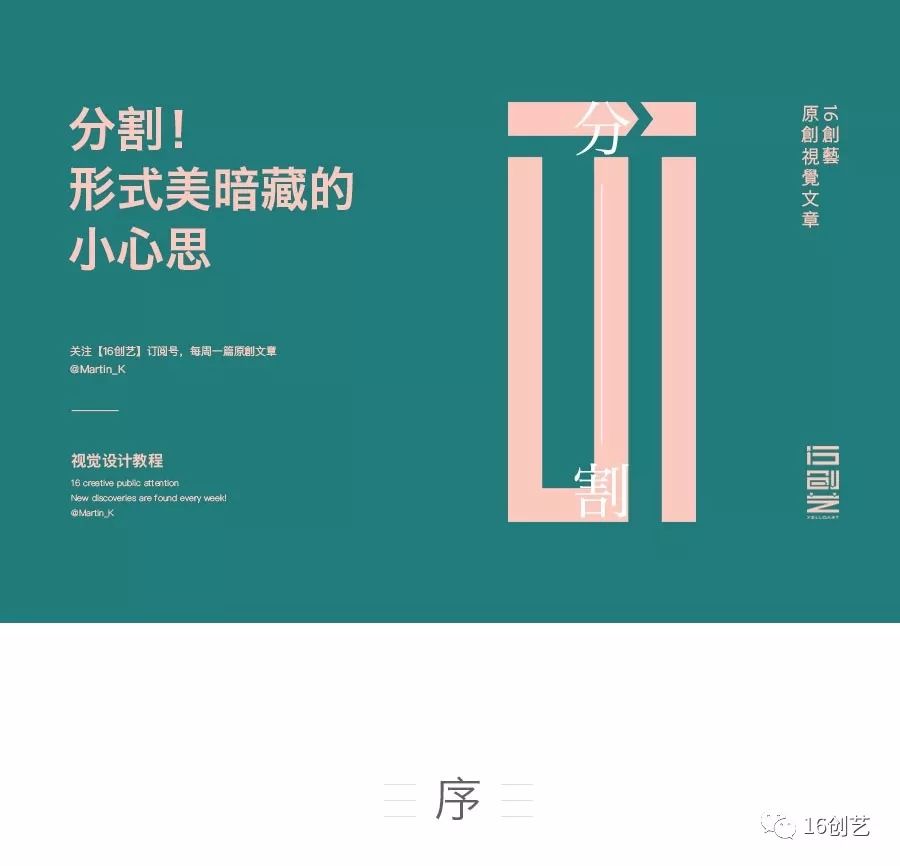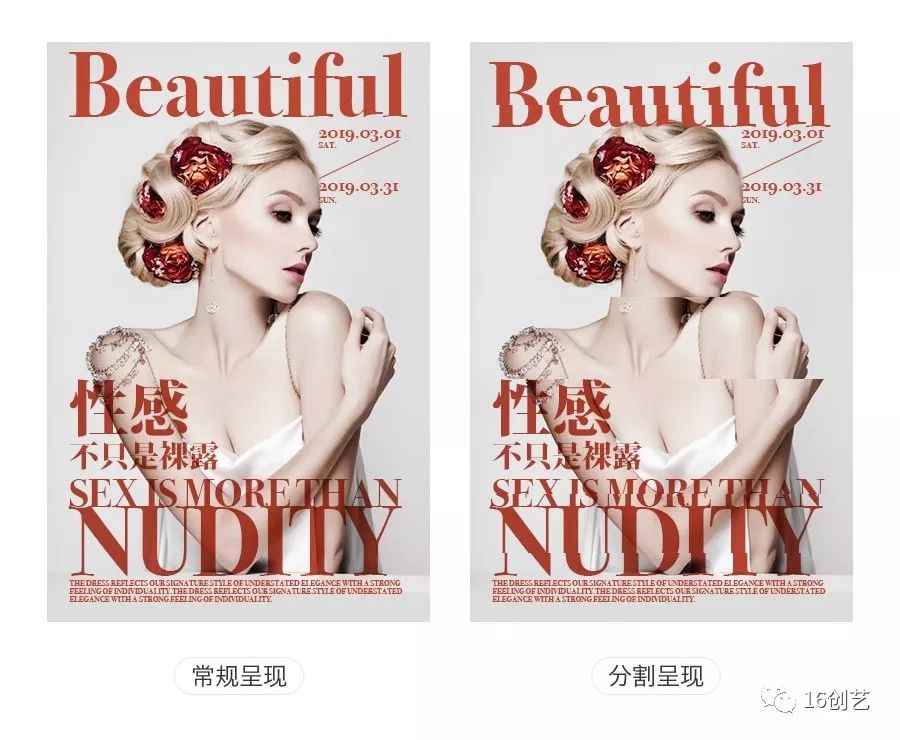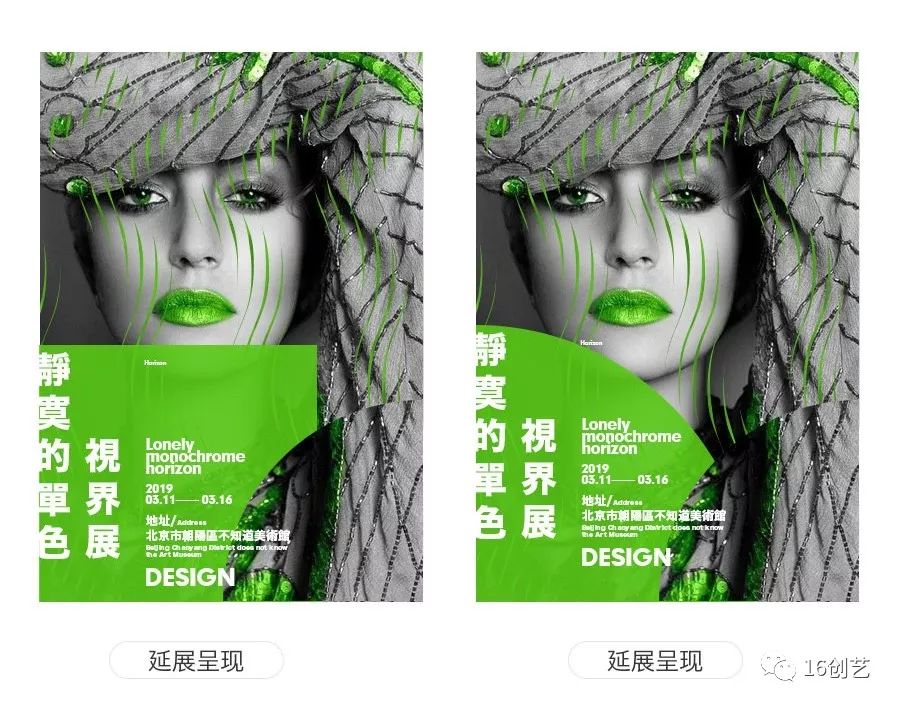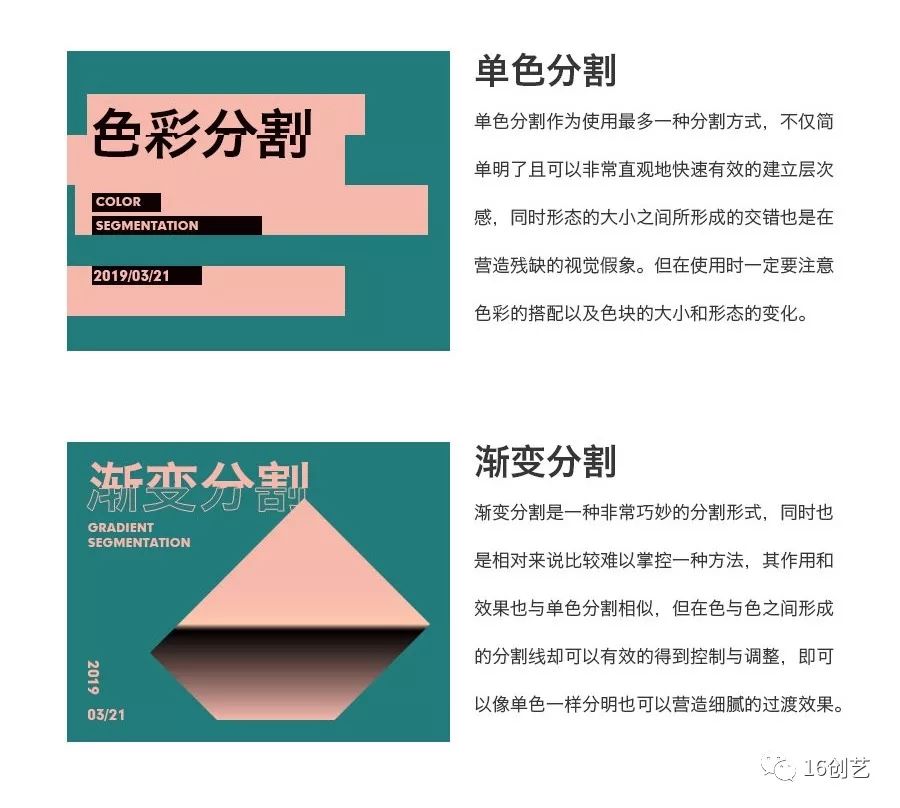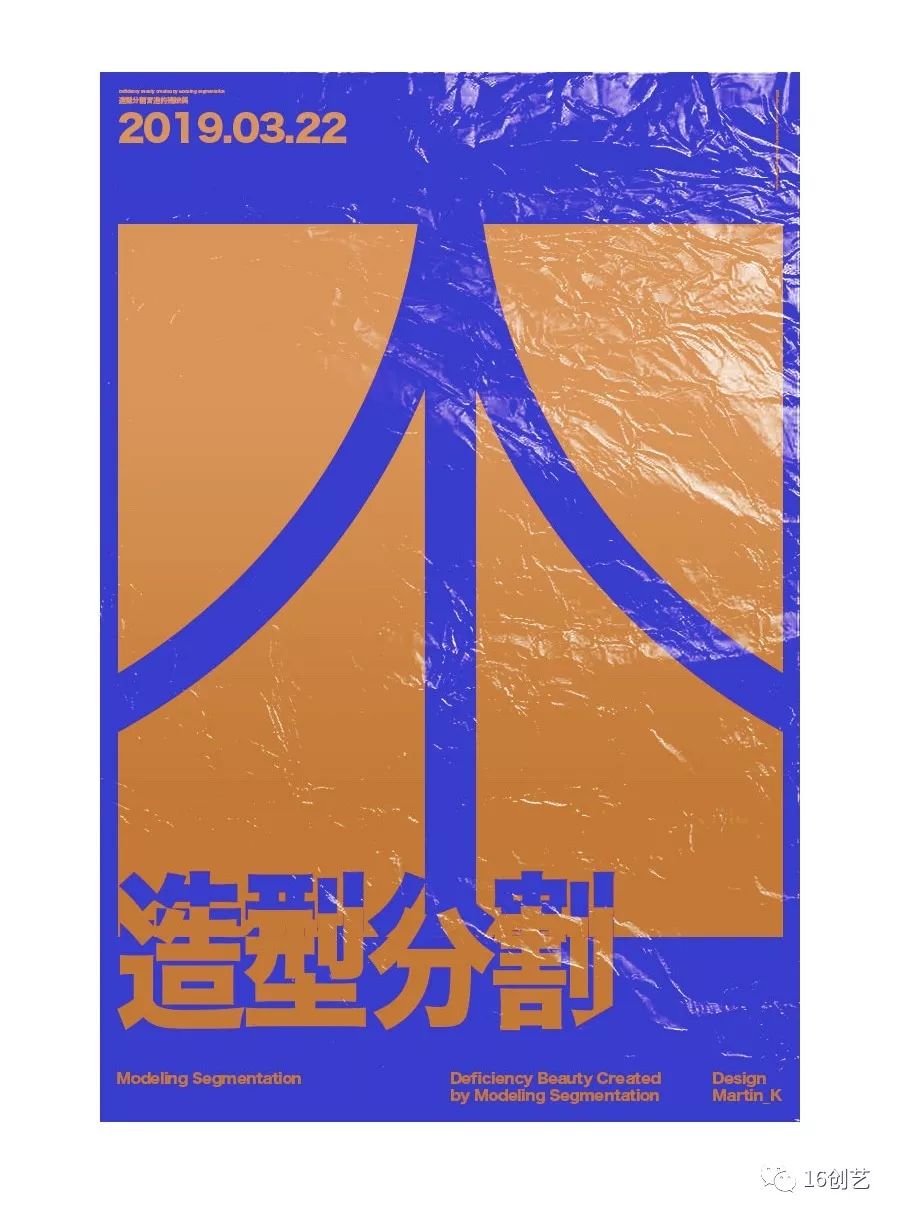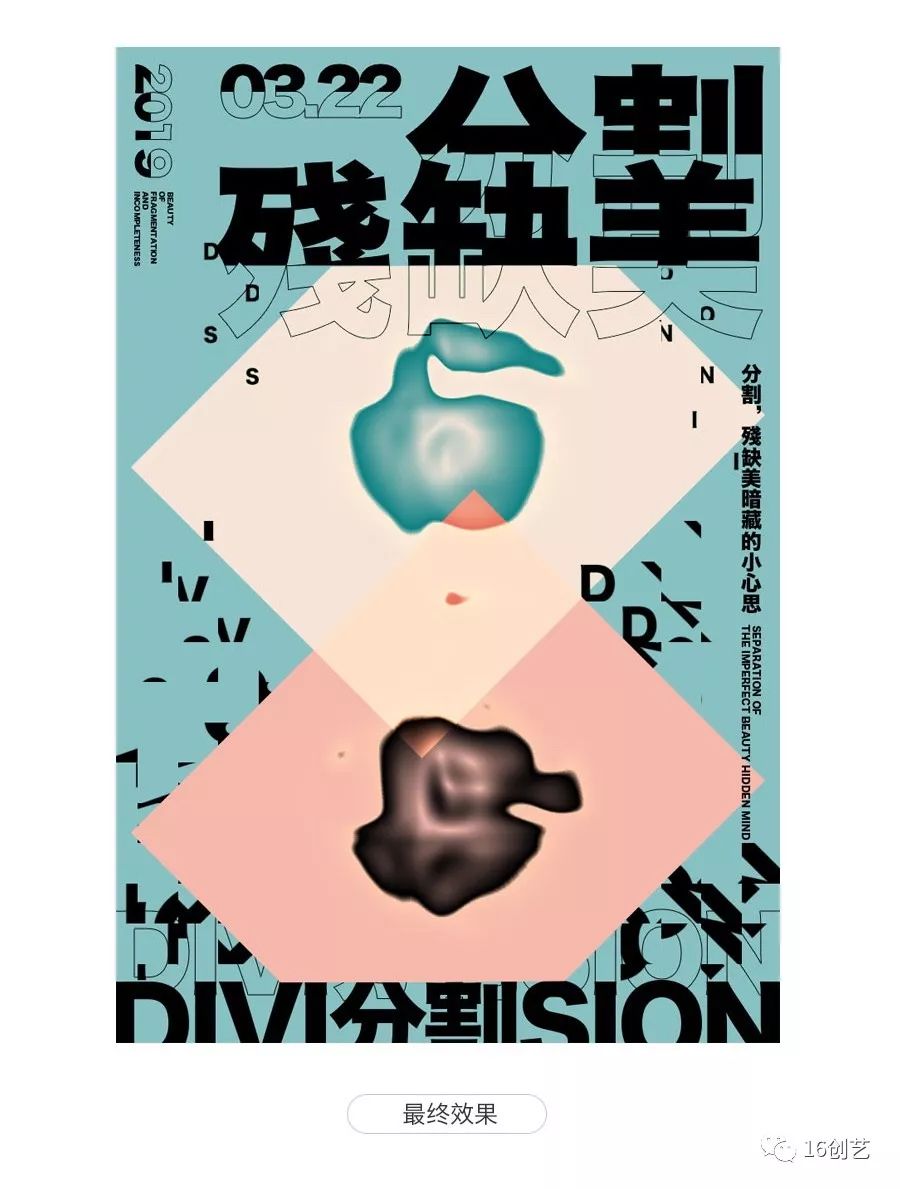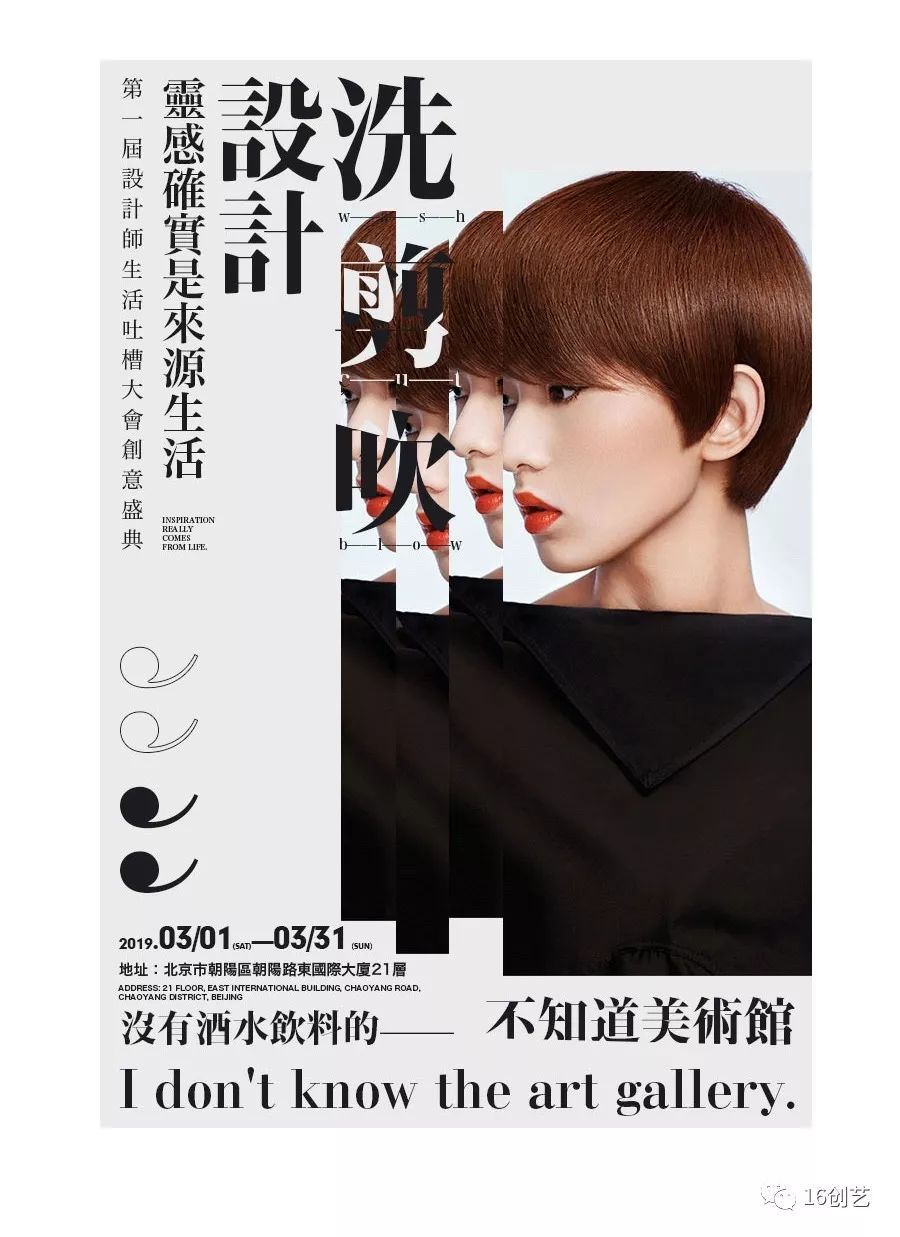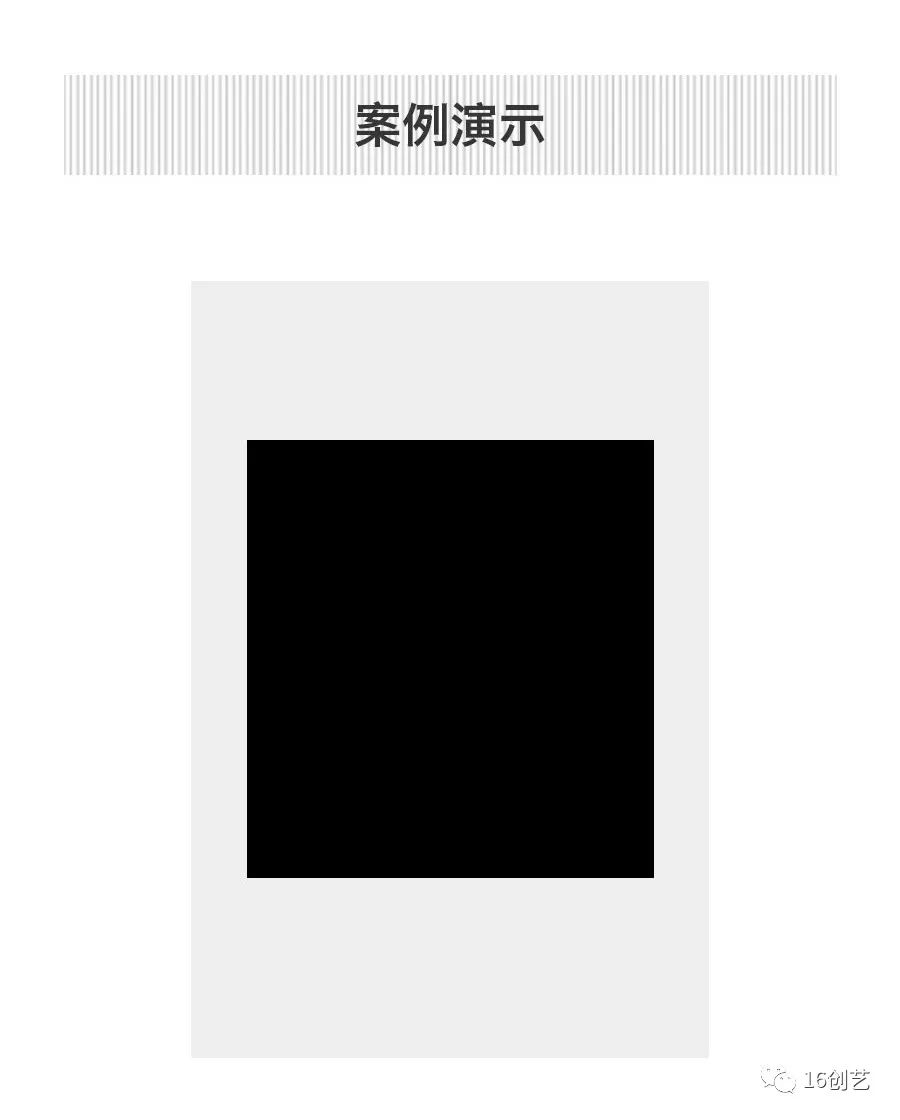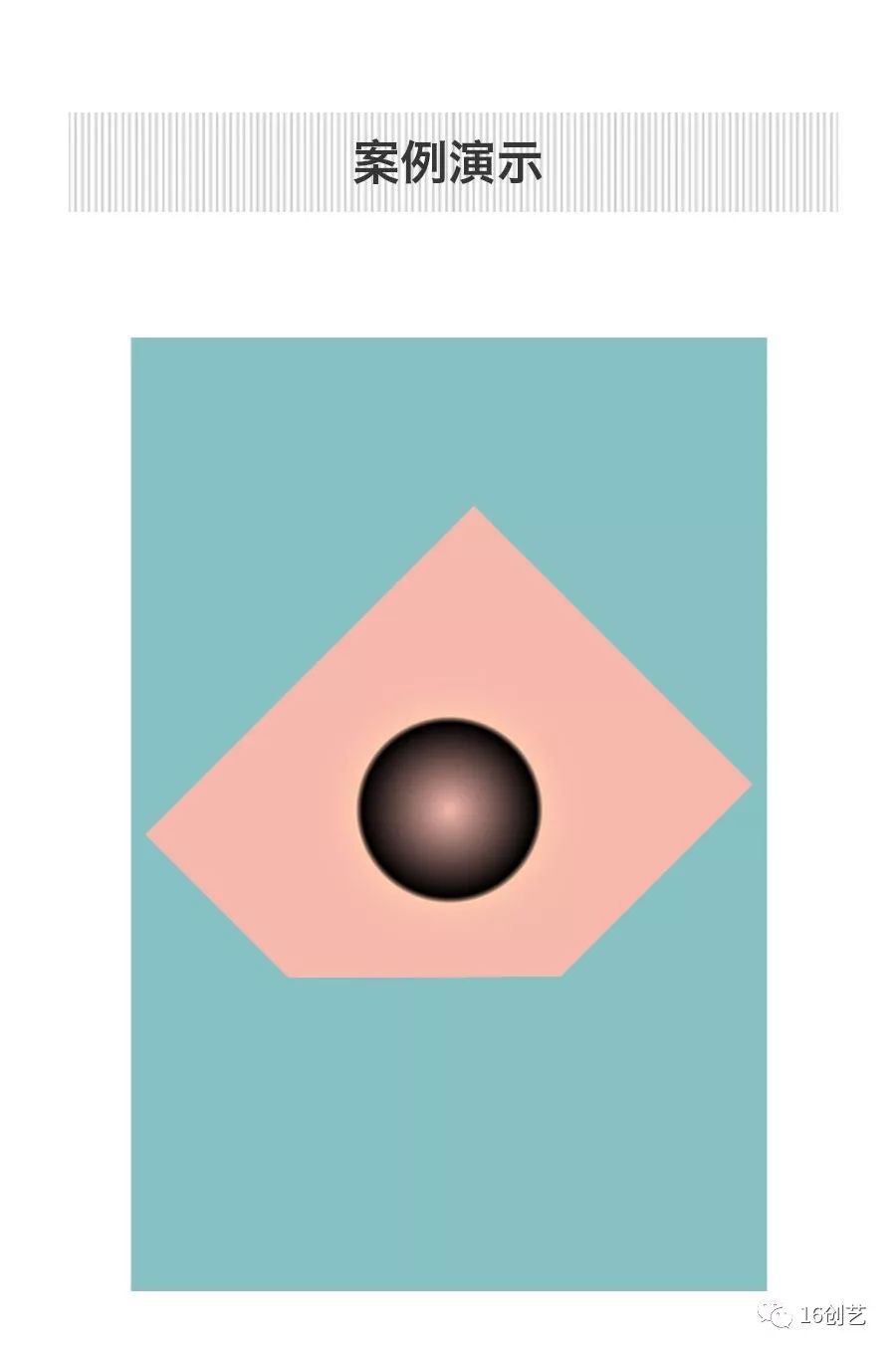
什么事分割?一篇文手把手教你所有的分割形式~
在日常生活中我们经常会看到破裂的事物,甚至在我们一不小心的时候就会把喜爱的杯子掉在地上摔碎了,或者在生气的时候把东西给撕烂,而这些看起不起眼的事情亦或者是人们在发泄情绪时的行为所产生的结果,在艺术领域却是有着不同的作用和价值,甚至是成为艺术创作者的神秘武器,而对于设计创作者来说则是把这种捕捉到的瞬间美以切割艺术表现的手法定格在创作的作品当中,用于表达和记录生活中因某些破坏行为而产生的残缺美,同时也是在遵循一定的设计准则、视觉感知的基础上对画面中出现的元素加以破坏,更好的演绎残缺美营造画面冲击力,也是基于小心思加法的基础上做减法。
分割即是在限定的空间内把完整的物体或者空间按照一定的方法加以破坏使其形成新的整体形态,并利用人眼自动补齐和联想的视觉规律,形成分而不离,割而不断的特点,营造一种残缺的、破坏的艺术美,同时也是提取生活中经常会出现的一种破坏后形成的自然现象作为常用的视觉表现手段应用在设计中,以更好的丰富艺术作品的创作,不仅可以营造残缺美还可以更好的赋予作品想象的空间,同时也是设计中极具细腻小心思的体现。
空间分割就是我们经常会提到的版式编排设计,即是在限定的空间内出现的视觉元素所摆放的位置无形中形成的分割,而没有被元素涉及到的地方就是所谓的留白,空间分割既不受元素形态的限制,也不受元素多少的限制,是以元素所占的空间面积大小形成的划分方式,是一种无形的分割呈现,也是最容易忽略的。
对于分割来说另一个特点就是对具体的视觉元素进行分割使其以新的视觉形态呈现,形成分而不离,割而不断的形式美,在对整体空间进行有效分割之后又对元素进行可视化的分割,以促进视觉感知营造层次分明的破摔视觉美感,同时也有助于进一步对分割后的局部元素形态进行刻画,以更好的贴合画面需求。
另外有时候为了营造更加鲜明的视觉感知区分,通常会把空间分割与元素分割同时以可视化的形式呈现,让观者较为快速的获取相应的信息,并有明显的切割线使之层次分明给人一种秩序的稳定感。
在常规的视觉呈现下,整体的画面只是对空间进行有效的分割,但对于单个的视觉元素来
说却没有很好的视觉表现,而对于视觉画面来说,不仅仅只是对空间的分割,更重要的是
对每个视觉元素的严格要求以点带动面的视觉表现才能更好的表现出精致与细腻的视觉效
果。
而当融入分割的表现形式后可以看出,分割不仅仅只是以横平竖直的分割线才能对空间和元素形成有效的分割,还可以以不规则的切割工具和手法实现分割以结果为导向的目的,其中就包括我们经常会使用到的肌理元素表现就像画面中最终呈现的视觉效果一样,不仅是分割也是利用分割的原理对元素进行深入的刻画。
从案例中可以看出,分割的形态变化是受切割工具的形态所影响,使用带有波纹的线条对文字分割之后会呈现出波纹的形态效果,同时还可以对分割后形成的若干形态进行局部的调整和变化。
直线分割作为最常见的一种分割形式,是把平面物体切割成几部分后所产生的切割线为直线,不管是在生活当中还是在设计大多数的分割都是以直线对物体和空间进行切割,给人一种规整且有序的视觉感受,在不失识别度的基础上把分割后的部分进行删减还可以营造残缺的视觉美感,同时还保留了分割线赋予视觉元素联想的空间,不管是对元素或者空间都是非常简单且使用的一种方式,但大多数设计者却很容易忽略减去部分后元素所留下的空白与空间之间的关系。
很多时候在受主体和信息限制的情况下很难融合创意,甚至是不能够对主体和其他元素进行过多的刻画和修饰,尤其是在以人物为主体的画面中,过多的创意和形式表现会降低人物的识别性和自身的特点,最终大多数会以常规的形式作为效果呈现,而编排上虽然也是依据网格对空间空间进行划分,但却没有视觉美感。
而当对主体和元素融入分割的表现形式时,对空间而言无形中会营造出多重空间错位的视觉假象,给人一种具有层次的感觉,在保证元素可识别的基础上营造一种视觉假象的创意,同时分割线以以直线的形态呈现传递出干净利落且整齐的感觉,在发挥分割多重作用时也赋予画面形式美。
另一种变化则是把分割后的部分适当的进行减去,以求更好的让元素与空间进行融合,尤其是在人物主体顶部的文字进行删减之后营造出一种叠加的视错觉,而下面的英文与英文之间在调整过间距之后进行删减,不仅可以有效避免多余的视觉感知,并以分割线为基础营造重合的、具有前后关系的层次感。
曲线分割是在进行分割时其切割线以连绵不断具有起伏的视觉形态呈现,是基于直线分割的形态变异,流畅的曲线通常给人们一种波动且极具艺术感的视觉感受,同时也比较贴合人类的情感变化波动,而在我们的生活中常见于建筑设计上面,以流畅的线条外观形态营造优美的艺术表现,而在平面设计中曲线分割由于气质的限定却很少被使用,但如使用恰当却可以营造别具一个的视觉美感,无形中为作品增添了艺术感。
在常规的情况下主体和其他元素不做任何的变化和处理,以文字自身的对齐方式形成无形的分割线,看似比较规整的画面却显得过于平淡,同时文字元素在主体较为饱满的画面中也不能够展现的那么完美,给人一种像是把文字贴在上面的感觉,对于整体的画面而言即缺少创意性,也不能够很好的表现出较强的视觉效果。
在此基础上从人物主体的服装上提取出曲线并与之融合,在贴合主体气质的同时丰富人物的情感同时在文字信息处加入四分之一的圆使图形的边缘曲线对主体人物进行分割,并对图形进行适当的曲线修饰,不仅可以很好的营造层次感和空间感,在贴合整体画面时也赋予文字一定的情感更好的传递信息。
在整体基本框架不变的情况下,以利用矩形色块对人物主体进行分割,同时对矩形又进行曲线的分割,使曲线的分割线与直线的分割线进行交叉,即可以保证曲线的情感表达,同时也可以表现出干净利索的感觉,使画面刚中带柔,而直线的分割线也可以为对齐提供很好的参考点。
与此同时还可以在曲线的基础上使曲线与曲线形成交叉的分割,虽然少了直线的干脆,但却是贴合画面整体的视觉效果而进行的形式延伸,以此来提升画面的视觉冲击力,同时交叉处也形成了鲜明的残缺美并赋予了画面更多的联想空间。
分割营造的残缺美是对元素进行设计手法的添加进而切割掉部分元素以空间进行填充,是利用视觉感知的自动补齐营造残缺美,并以割而不断的特点赋予想象的空间,在可识别的基础上给人以整体中带有层次变化的感觉,同时也是营造残缺的形式美强调视觉冲击力,对元素而言加的是方法和手段,减去的是自身的肉体。
如案例所示,对主体元素进行分割的手法添加之后随之把分割后的部分元素减去,在与空间进行融合的同时营造一种站立在空间的假象,并以分割线作为视觉的起点,给人一种像是从空间中生长出来的感觉,与此同时主体也没有失去自身原本的面目,还赋予了一定的联想空间。
而当把主体分割成大小不一的几部分后可以看出,即使在减轻主体自身的视觉重量,使主体自身具有一定的透气性,营造强烈的视觉形式美时,元素所减去的部分仍然不影响整体的识别性,还为其无形中营造分明的层次感,哪怕时最细的分割线也是对元素减去的一部分。
另外需要注意的就是,在使用分割时一定要注意元素的视觉重量,左边的案例是对元素下半部分进行分割使其视觉重量减轻,给人一种向上要飘动的感觉,而右边的案例则与之相反,给人一种下垂的感觉,如不细心处理在与其他元素组合在一起时很容易使整个画面失去平衡,降低视觉的感受体验。
为使得分割后的元素在重量上得到一定的视觉平衡,针对左边的案例上部分适当的删减一部分,而把右边元素中间的分割线加宽,使视觉集中在最大的空隙中以此消除上轻下重的视觉偏差。
分割作为设计中比较基础的手法之一,在一定程度上也是应用的最为广泛且最为实用的方法,不管是在版面空间的划分当中亦或者是在对元素进行手法和技巧的应用当中都有着非常出色的表现,而常用的方法却也是的大家经常会忽略的方法,其主要是容易受到表面形式的影响,而失去对本质的分析和总结,对于版面来讲,我们经常提到的黄金分割,网格系统等等亦或者是对元素的切割都是使用分割的原理进行的形式演变,而本篇文章提到的残缺美也是在基于分割表现上做的形式变化,亦是切割和分割的直观表现,其方法和手段大致可以分为归纳为3点。
色彩分割是区分内容层级,建立层次感最有效的、最直接的方式之一,也是最为醒目且具有突出作用的设计手段之一,很多时候我们在选择使用不同的色彩时,就已经是在不知不觉中对画面空间使用了分割的设计手段,但对于初学者来说却只把重心停留在色彩的选择上,而忽略了承载色彩物体的大小占比与形态在画面空间中所产生的视觉影响,却只是把色彩当作元素使用使之出现在画面中,导致对画面整体的空间把控不佳,难以很好的驾驭整体的布局,进而忽略色彩所形成的小心思。
在新建的画布当中将做好的主体置入,在这种情况下需要注意的就是,主体元素的色彩和背景色彩本身就已经存在区分,而主体下面缺少的部分就像是由背景色分割掉的一样,由此可以看出,除了色与色搭配之间的关系外,主体又再次的与背景产生了微妙的关系,使之在区分的同时还保留一定的关系。
图1:
把主体进行适当的处理然后复制一层改变其中一个主体的混合模式,两个主体分割掉的部分在空间上形成对称,而重叠的部分由于混合模式的改变也形成相互分割的效果,即保证画面平衡同时也凸显视觉效果。
图2:
接着把文字置入到画面当中可以看出,整体给人一种从上至下的感觉,上半部分较重,而下半部分较轻,同时文字掩盖了主体大部分使主体不能很好的展示出来,而要改变文字的大小则会使画面不够饱满。
图1:
接着对文字信息进行分割的适当处理,把顶部的文字使用渐变分割一分为二并使之重叠在一起,在保证识别的基础上即减轻重量又可使描边和实体形成鲜明的对比同时使分割部分与主体的残缺形成对齐,但主体部分却显空旷。
图2:
然后针对主体略显空旷的问题进行适当的修饰,用英文按照下大上小的规律随意的排列,并对其执行波浪的效果使其具有一定的切割效果,即符合画面的整体,同时也能很好的当作修饰并与底部文字形成关联。
几何作为设计中最基础的元素,也是使用频率最高的元素之一,画面中出现的所有元素都可以看作是几何图形的形态变化,色彩分割也是在基于几何图形的基础之上的色彩分割,其本身并没有任何太多的意义,需要进行不断的组合搭配才能赋予几何某种意义并使之发挥出不同的作用,而当发挥分割作用的时则可以以线条的形式和块状的形式使用对空间和元素进行分割营造一定的形式美感。
很多情况下我们拿到的主体或者找到的素材并不是那么完整,在很大程度上增加了设计者的工作难度,不管是对空间的把控亦或者是对主体的创意展现都受到了局限性,在这种情况下不妨试试运用分割类型的技巧,既可以贴合主体的切割,同时也增加了画面的形式美。
图1:
在新建的画布中以适当的矩形作为主体的载体,在保证可识别的基础上依次重复几次,使其以不同的大小分别展现主体,营造一种被分割的成几块的感觉,使其具有可控性以便我们对空间更好的进行布局。
图2:
然后调整主体的位置并把文字置入到画面当中进行调整,值得注意的就是顶部的中文与主体形成重叠使的文字不能很好的展现而人物主体最重要的眼睛部分也被遮挡起来,虽然主体在处理之后具有了形式美,但对细节还需调整。
图1:
首先对重叠在主体上面的文字加入色块分割使其在可识别的基础之上与主体的形式相呼应,然后适当的调整主体使其眼睛可以展现出来,在进行块状分割的情况下大多数是以剪切蒙板的形式,所以只需要调整主体即可。
图2:
块状分割的情况下可以随意的改变主体的位置和大小,如改变块状的载体则是对空间的布局以及占比等进行调整,但需要注意主体分割后的连贯性以及整体性。
新建一个画布,然后在画布中创建一个矩形,并调整至合适的位置,其主要目的就是对矩形进行造型的分割,即可保证矩形同时也能突出分割后的造型。
对矩形进行“木”字的分割后可以看出,矩形被分割了大小形状不一的图形而木字则保留下半部分,使得两个不同的造型合为一体,对矩形来说即是分割同时也是负空间的具象体现,这种也是造型分割最常用的一种方式。
然后把文字置入到画面中同时对下面的中文也对矩形进行造型的分割,使其切割后的空间具有文字的部分造型,在与文字形成呼应关系的同时也是增添了创意,整体虽然看起来简单但却使得画面较为丰富且发挥了分割的作用。
分割作为设计中的基础构图、表现手法、设计手段等,其作用和效果远远不止于此,但重要的是理解其中的原理并活学活用,在创作的过程不断的尝试即使是一种手法和手段,同样也可以演变出不同的视觉效果和创意,希望本篇文章可以帮助大家更好的了解分割,并对其有初步的认识,并不只是停留在对版面空间的划分上面。